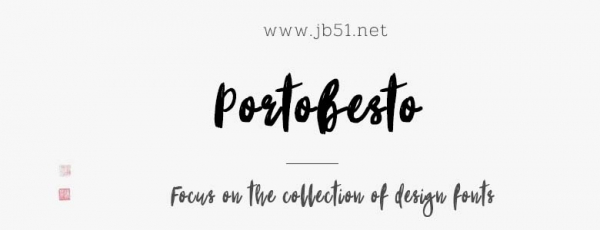
Portobesto英文筆刷字體,筆觸適中,書(shū)寫(xiě)流暢,具有很好的視覺(jué)感,適合應(yīng)用于藝術(shù)設(shè)計(jì)、平面宣傳設(shè)計(jì)、網(wǎng)頁(yè)設(shè)計(jì),書(shū)法字帖等領(lǐng)域。有需要的朋友快來(lái)本站下載使用吧。